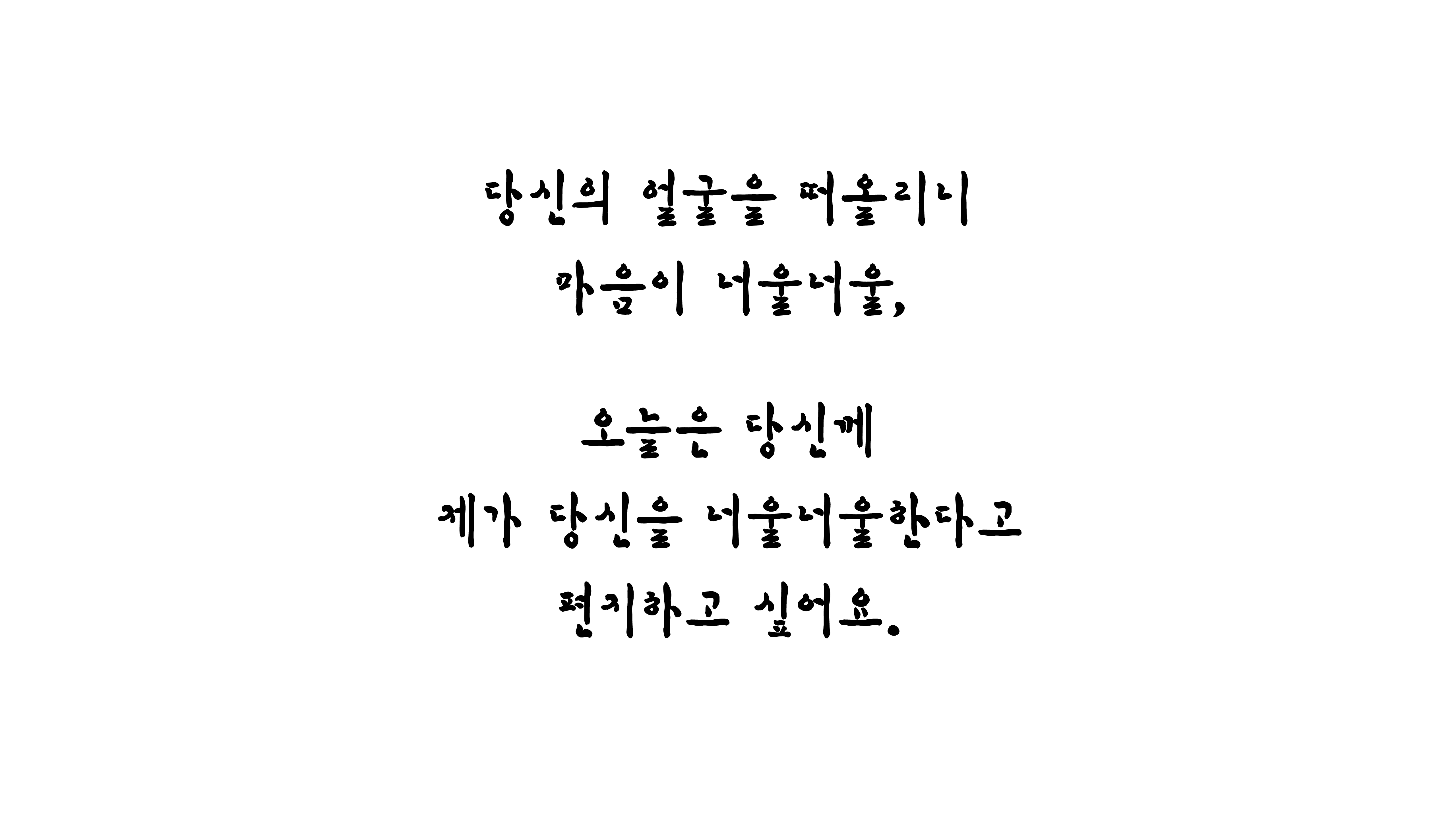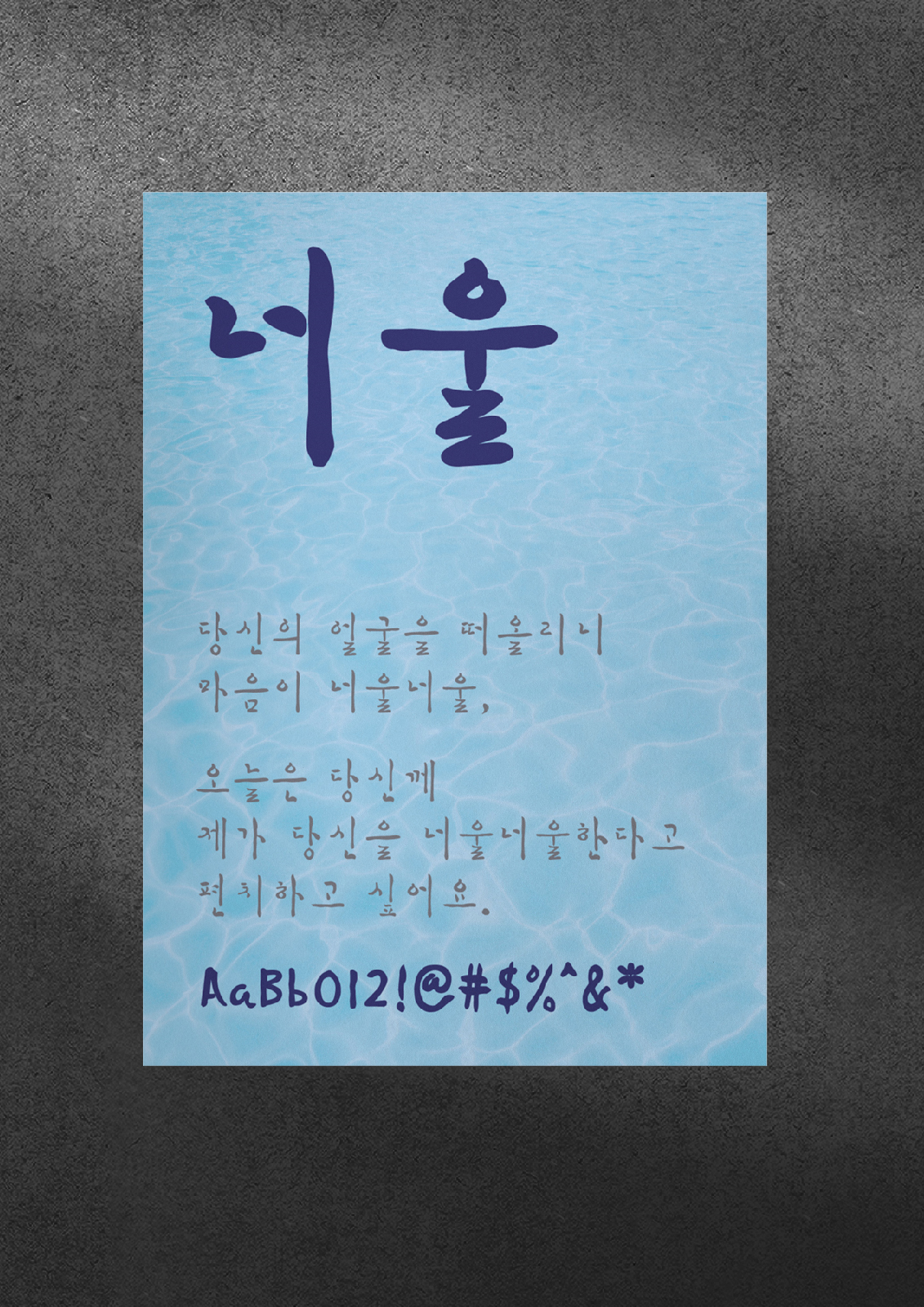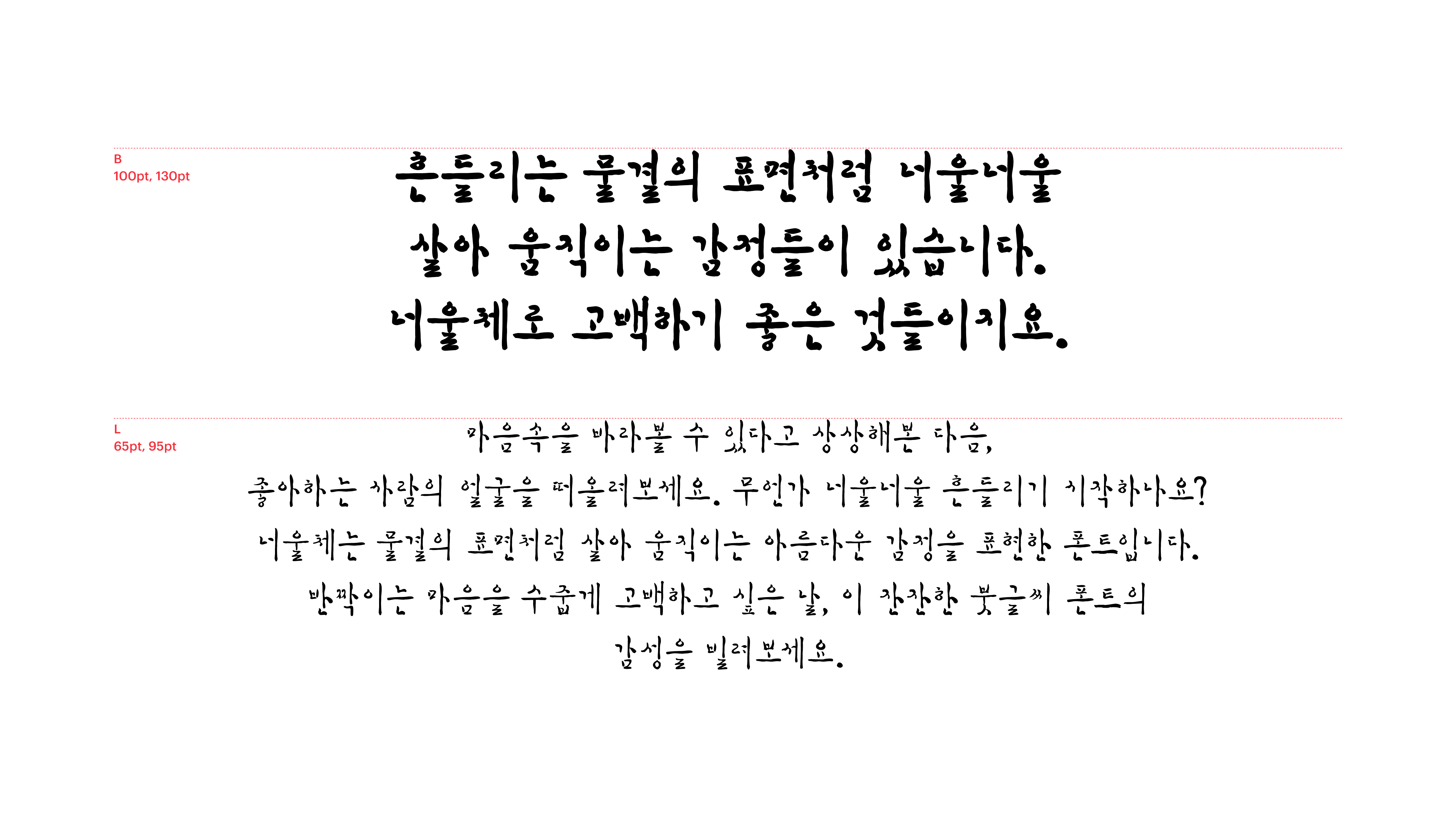
[손글씨]
너울
Yoon 너울
마음속을 바라볼 수 있다고 상상해본 다음, 좋아하는 사람의 얼굴을 떠올려 보세요. 무언가 너울너울 흔들리기 시작하나요? 너울체는 물결의 표면처럼 살아 움직이는 아름다운 감정을 표현한 폰트입니다. 반짝이는 마음을 수줍게 고백하고 싶은 날, 이 잔잔한 붓글씨 폰트의 감성을 빌려보세요.